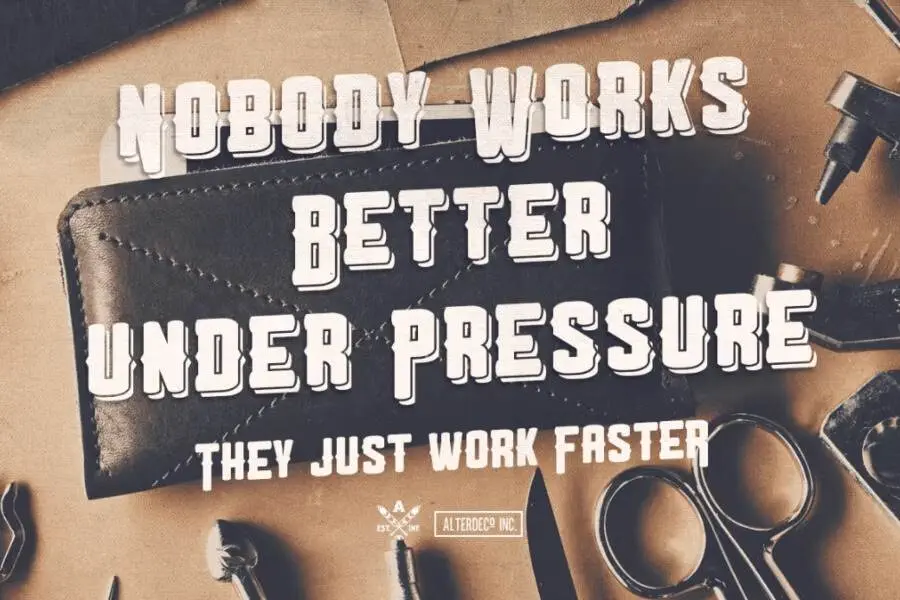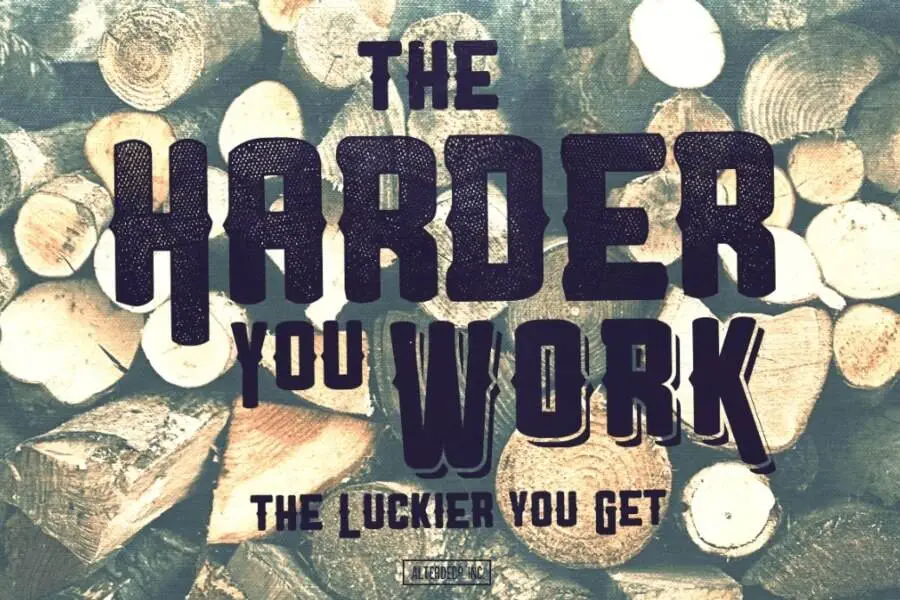
Font Boulden táo bạo! tất cả các mũ! hoàn hảo cho áp phích tuyên truyền của bạn, hoặc thậm chí là một thiết kế đồ họa hiện đại nhưng cổ điển. nó có sẵn trong 3 phong cách khác nhau mà bạn có thể chơi, phong cách sạch sẽ, grunge và bóng tối thông thường.